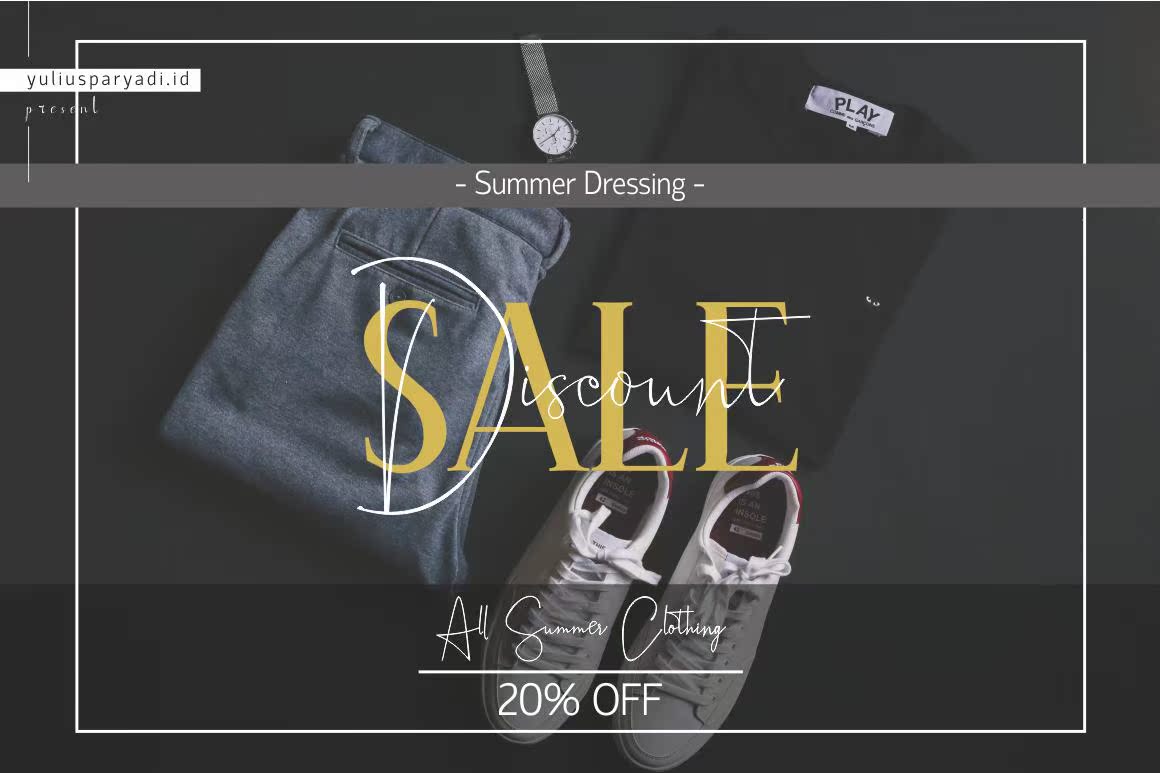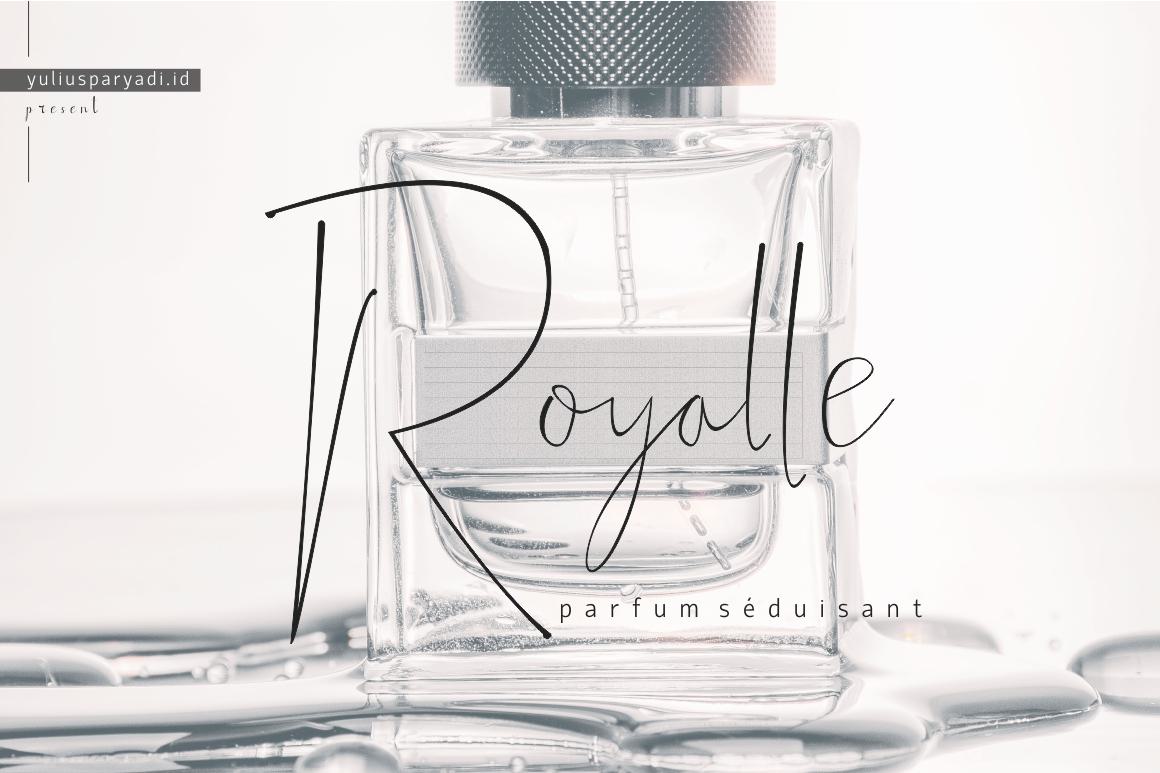
剪影幻影(SignatureStylish)是一种具有现代风格的自然签名样式。AgoodMatch Alloy将使其成为专业的侧面。确保它成为您设计的一部分。这种字体可读、吸引人且简单。这种字体适用于引用、标志设计、杂志、名片,以及其他许多设计项目。剪影幻影(SignatureStylish)是一种具有现代风格的自然签名样式。AGOOD Match Alloy将使其成为专业的背景。确保它成为您设计的一部分。这种字体可读、吸引人且简单。该字体适用于引用、徽标设计、杂志、名片和其他许多设计项目。